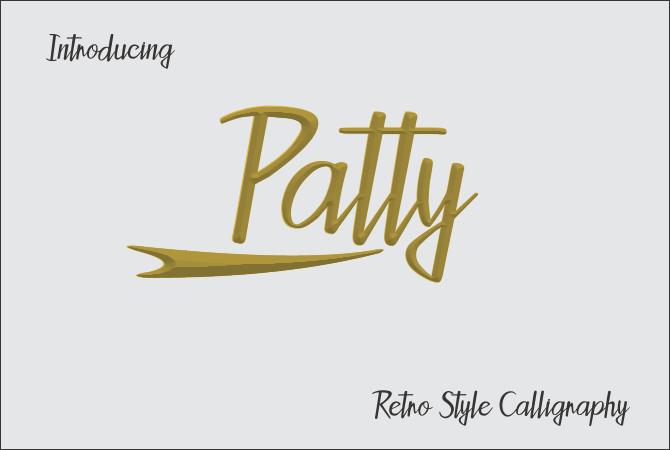
Introduzimos Patty Script Font, uma fonte tipo estilo calligrafia com um sabor retro. Este design foi criado por Jaime Rangel Castro e compartilhado pelo mundo através de sua beleza única. Esta fonte tem a capacidade de dar vida a textos chamativos em designs digitais variados, especialmente quando usada para elementos de marca ou ilustrações gráficas. Suas curvas fluidas e linhas finas fazem dela um excelente candidato para aqueles buscando personalidade em seus projetos. Seja você designer, publicitário ou artista digital, Patty Script Font certamente trará uma nova dimensão ao seu trabalho.